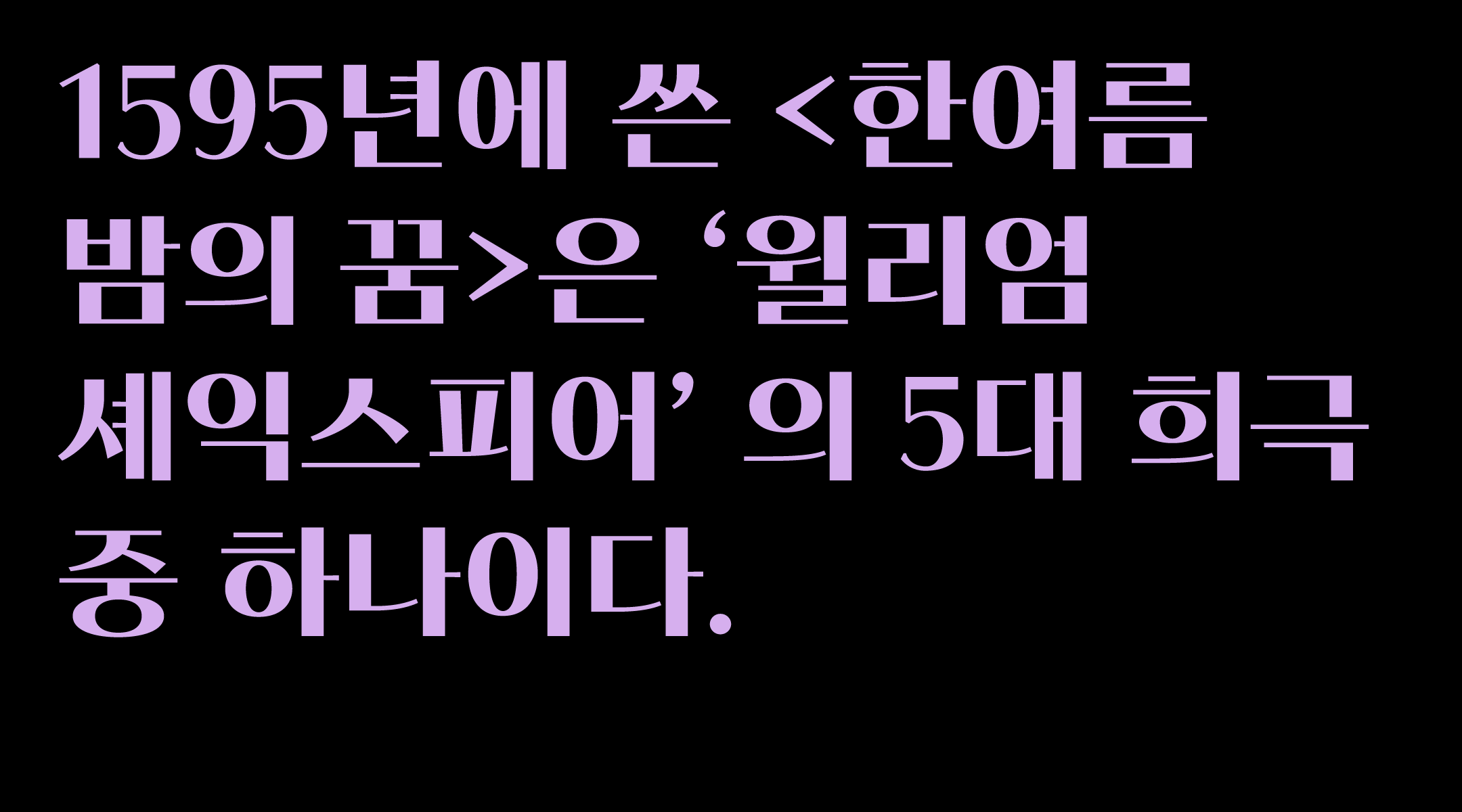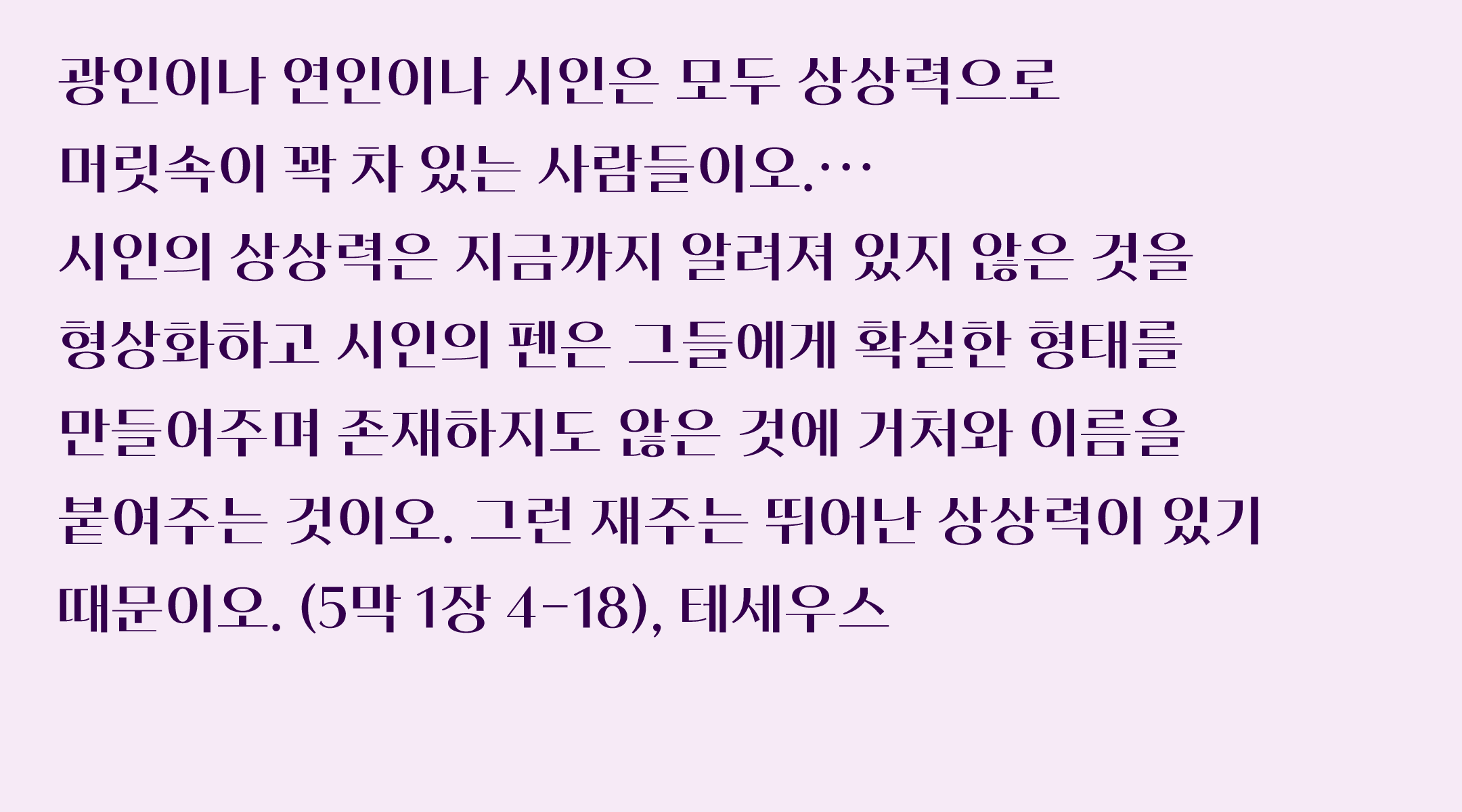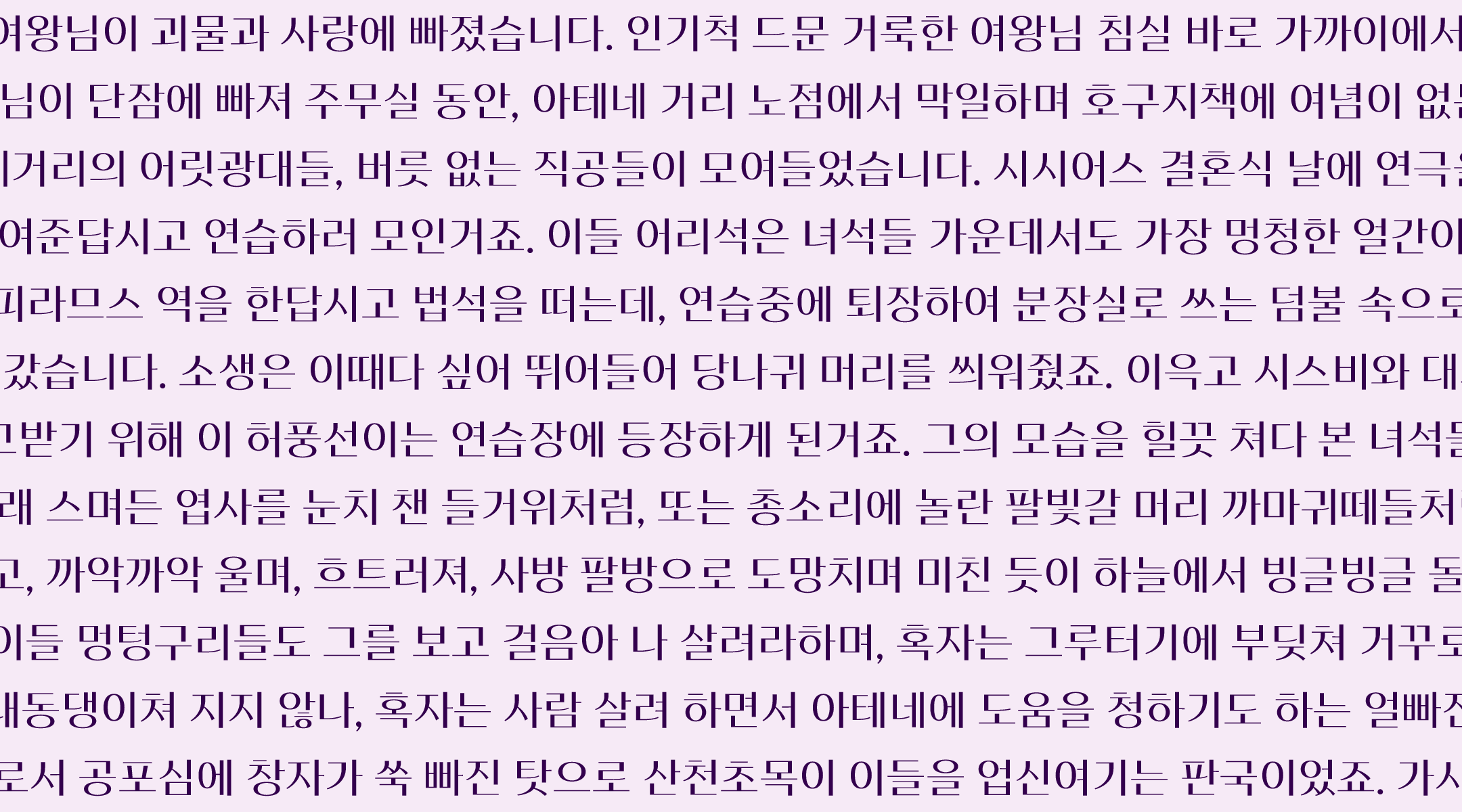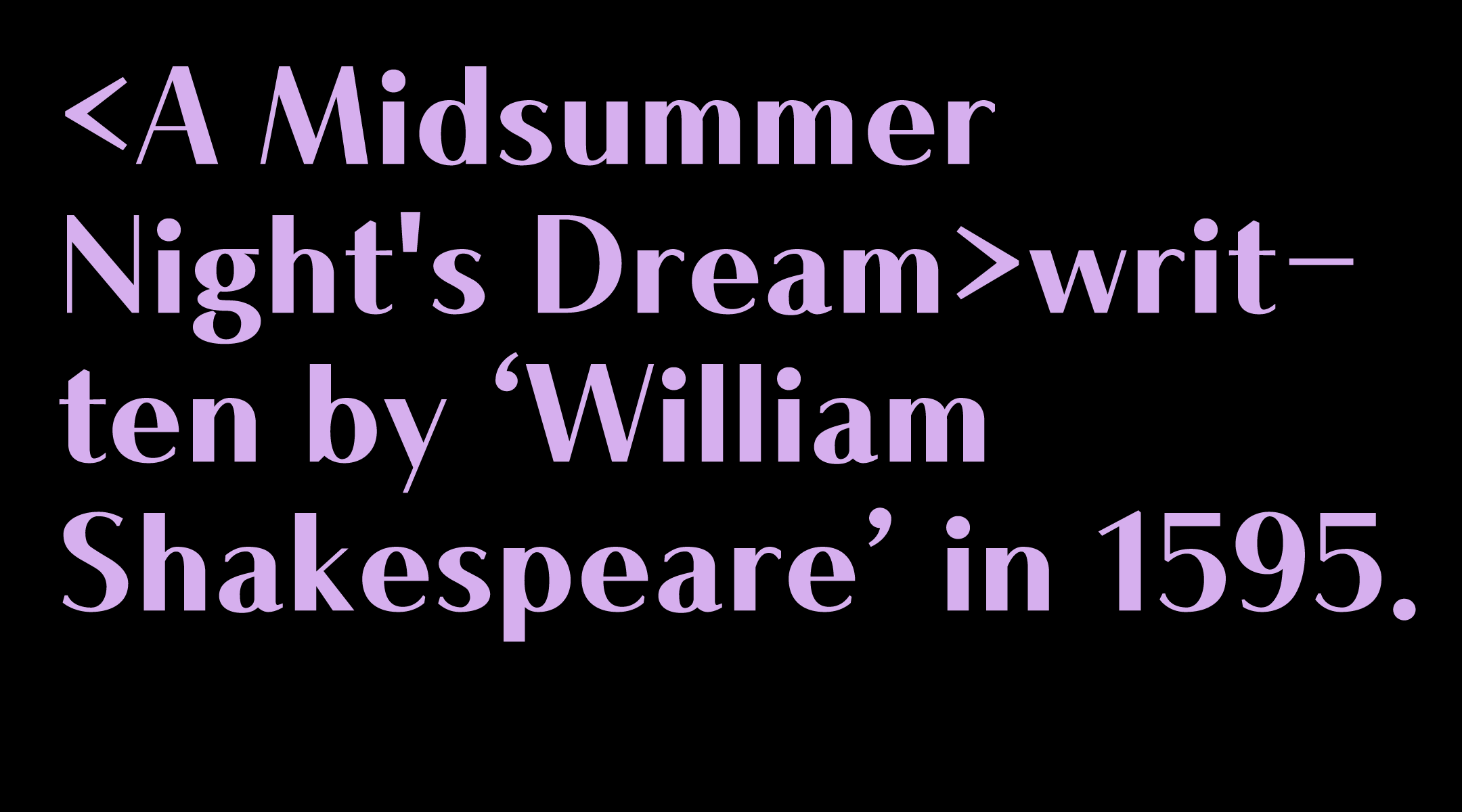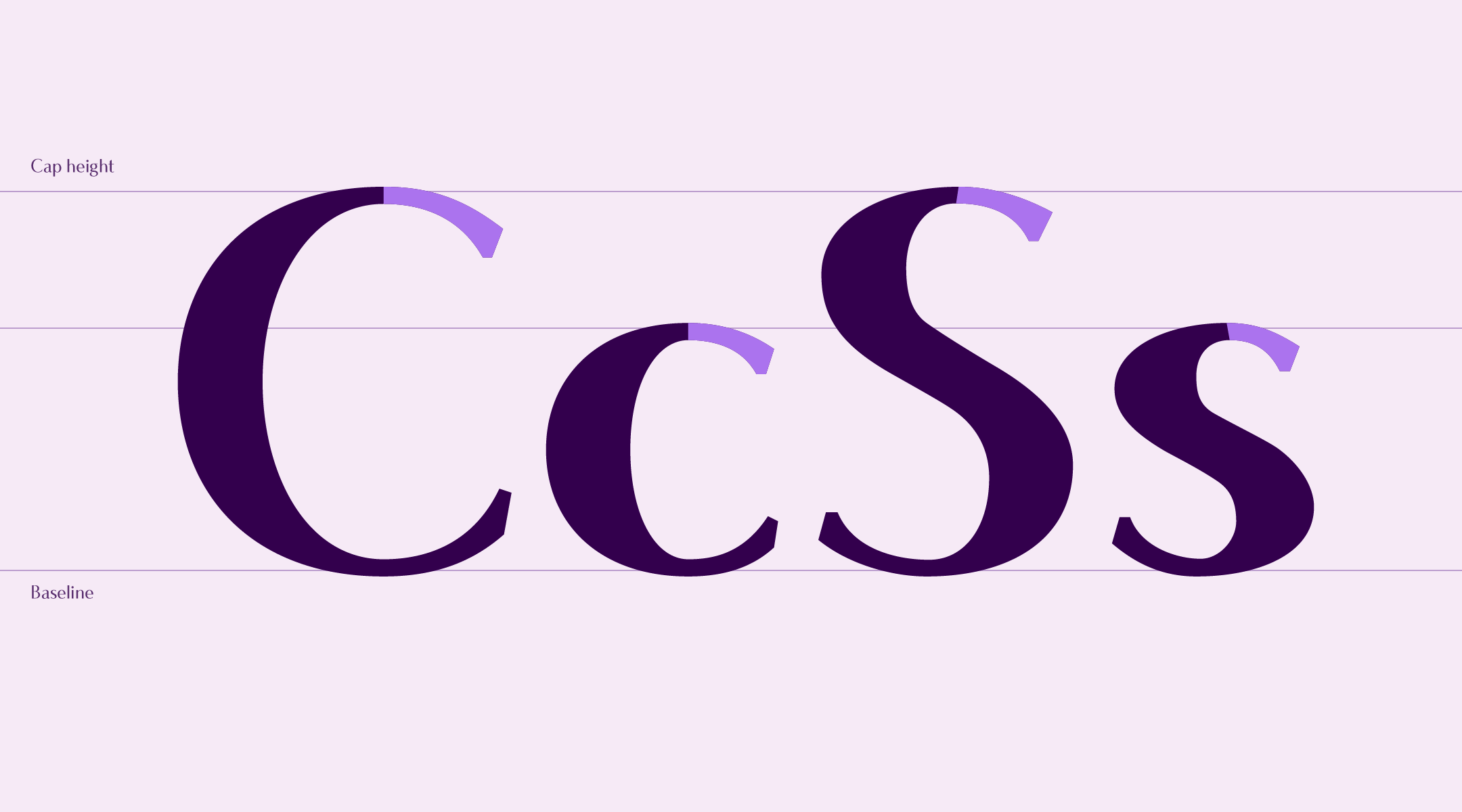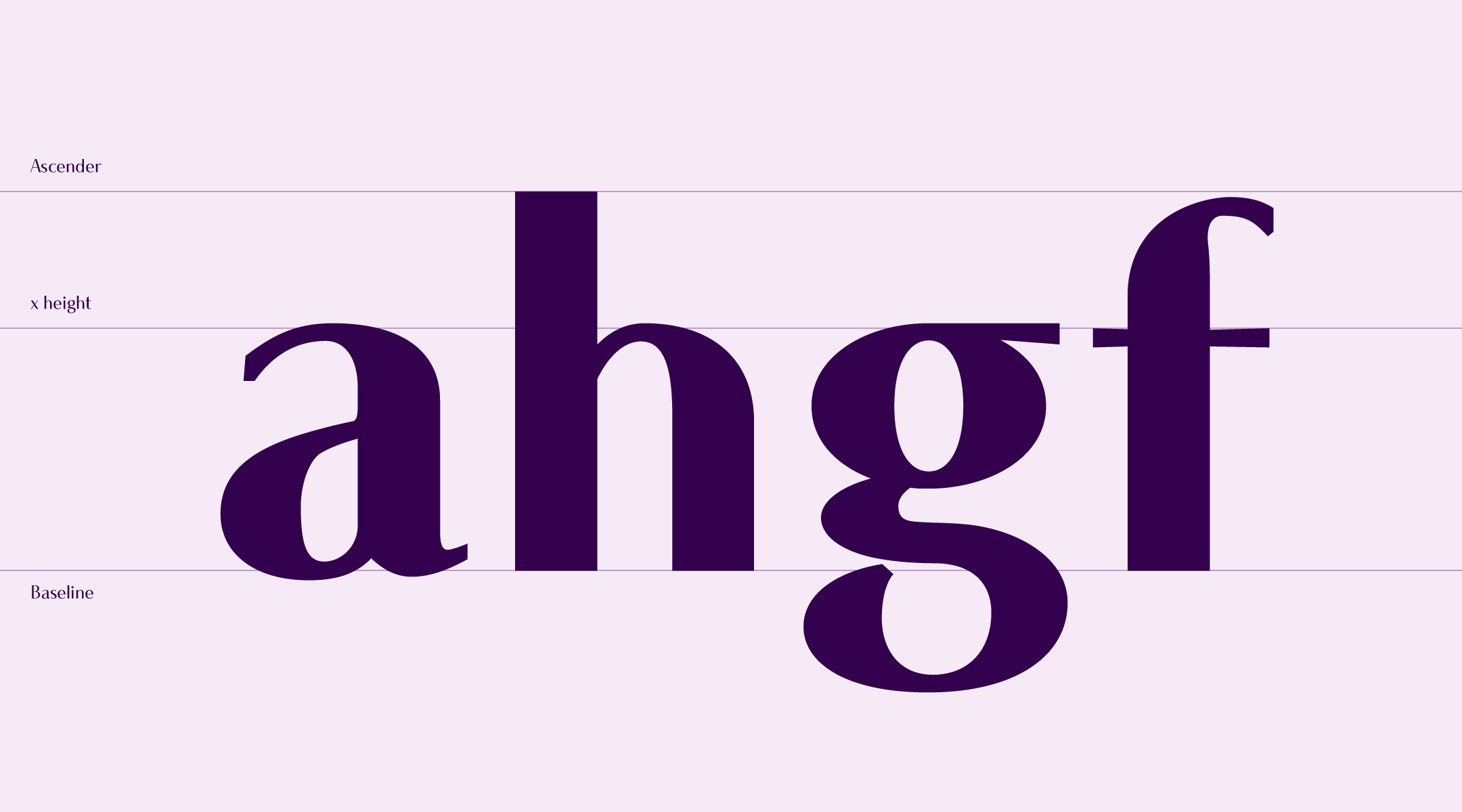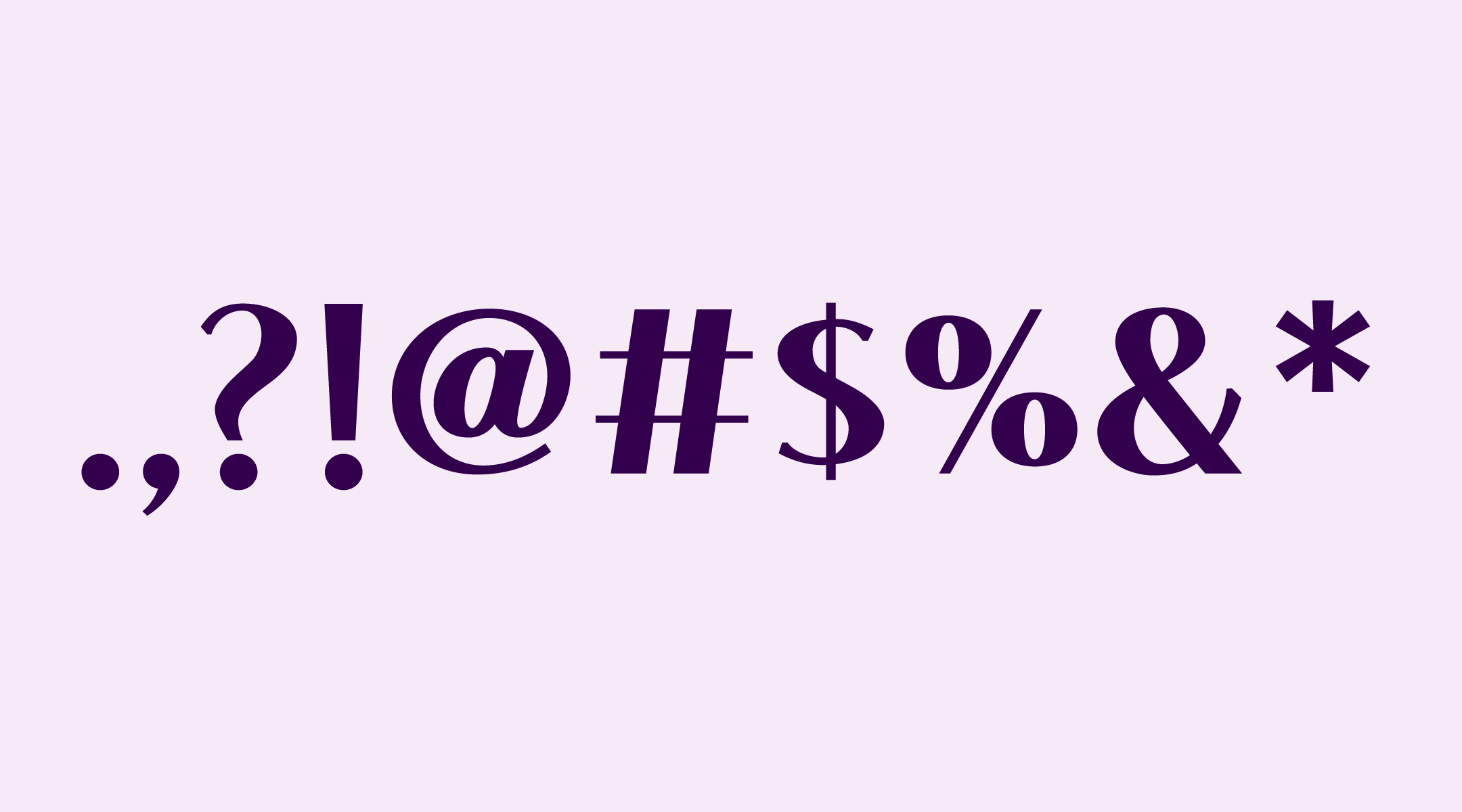
직지폰트의 신서체 <j에피소드>를 소개합니다.
J에피소드는 일상에서 일어나는 크고 작은 이야기와 함께 하고자 기획된 폰트입니다.
에피소드의 어원은 그리스어로 에페이소도스(epeisodos: 추가해 넣는 것)로 노래와 노래 사이의 대화 부분을 나타내는 것에서 시작되었으나
오늘날에는 장편 시리즈 작품의 각’회’를 의미하기도 하고 완결된 '짤막한 이야기’의 뜻으로 많이 사용하고 있습니다.
J에피소드 그러한 우리의 이야기에 우아하지만 정제된, 친숙한 목소리를 낼 수 있는 폰트가 되었으면 합니다.
윌리엄 셰익스피어의 작품 중 가장 환상적이고 몽환적이며 작가의 상상력이 가장 잘 발휘된 작품으로 알려진<한여름 밤의 꿈>.
<한여름 밤의 꿈>이 전달하는 사랑과 환상의 이미지, 인간과 요정과 신의 대사를 통해 <j에피소드>를 감상해보세요.
한글 디자인 특징: 에피소드는 그래픽체의 계보를 따르지만 자소의 형태 디자인 및 획을 곡선과 직선의 적절한 분배하여 우아하며 세련된 인상을 줍니다.
‘ㄱ,ㅅ’ 계열 자소에서 보이는 독특한 곡선감은 글자의 풍성하고 우아한 느낌을 강조하며, 가장 큰 분위기를 형성합니다. 초성 ‘ㄴ,ㄷ,ㄹ,ㅌ,ㅍ’의 자소는 일부 글자에서는 '곡선'을 띄지만 받침 글자에서는 '직선'으로 처리해 '깔끔한' 이미지를 보여줍니다.
한글 자폭은 '모임 꼴' 별로 각기 다른 넓이를 가지고 있습니다. '바'에 비교해 획이 많은 '빠'는 더 넓은 자폭을 가져, 글자의 공간 설계를 효율적으로 디자인했습니다.
라틴 디자인 특징: 휴머니스트 산스(Humanist sans) 양식에서 보이는 고전적인 느낌과 현대적인 감성이 어우러집니다.
'C,G,S' 같은 일부 글자의 작은 세리프 장식이 특징입니다. 대부분 획에 장식이 생략되어 획대비의 강렬하고 '깔끔한' 인상에 집중했습니다.
대소문자 디자인은 한글의 분위기와 어울리는 형태를 가지고 있습니다. 'B,C,D,G' 글자에서는 곡선미를 살렸고, 'K,M,N,V' 같은 꼴에서는 직선의 느낌을 부각시켜 한글처럼 곡선과 직선이 어우러지도록 디자인했습니다. ‘J,Q’가 이와 같은 분위기를 글자에 담아내고 있습니다.